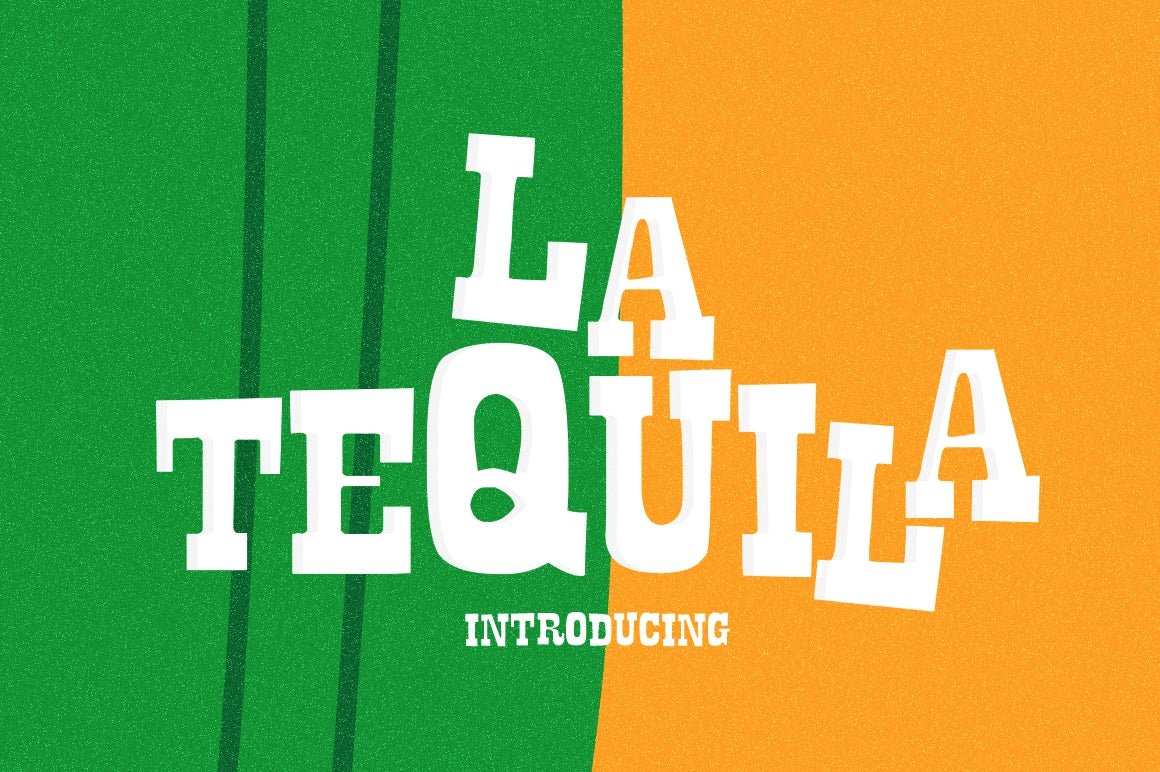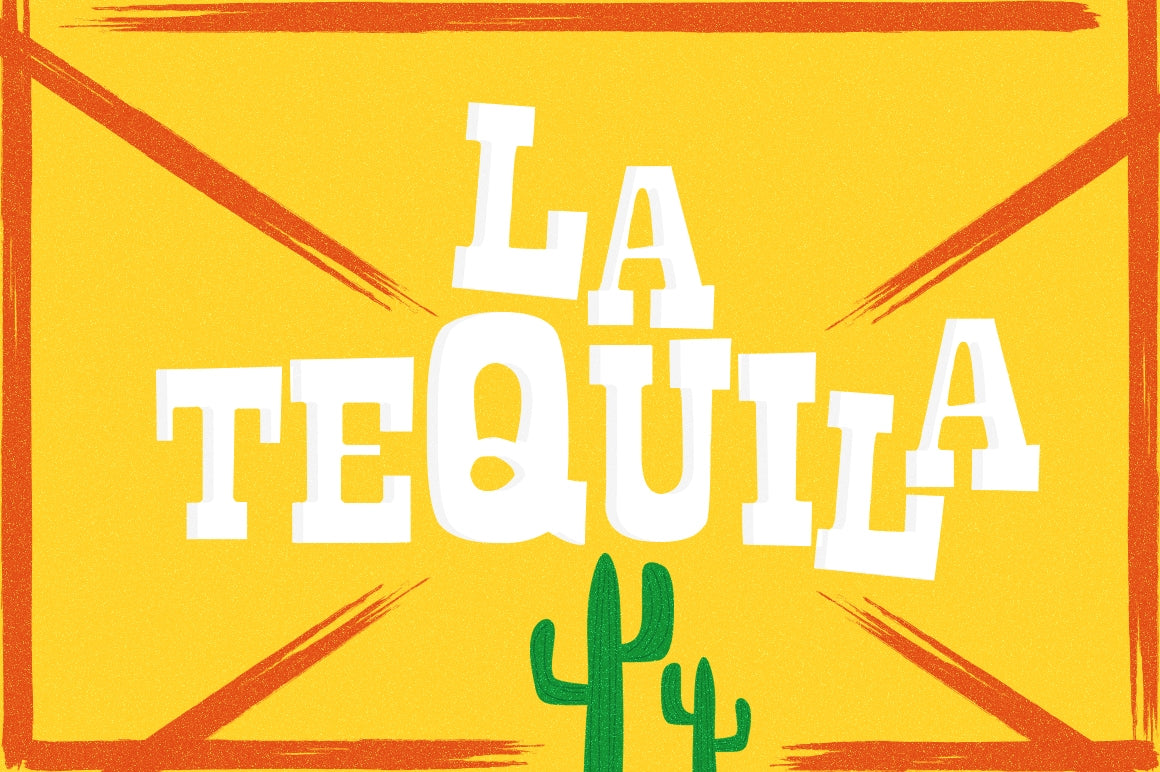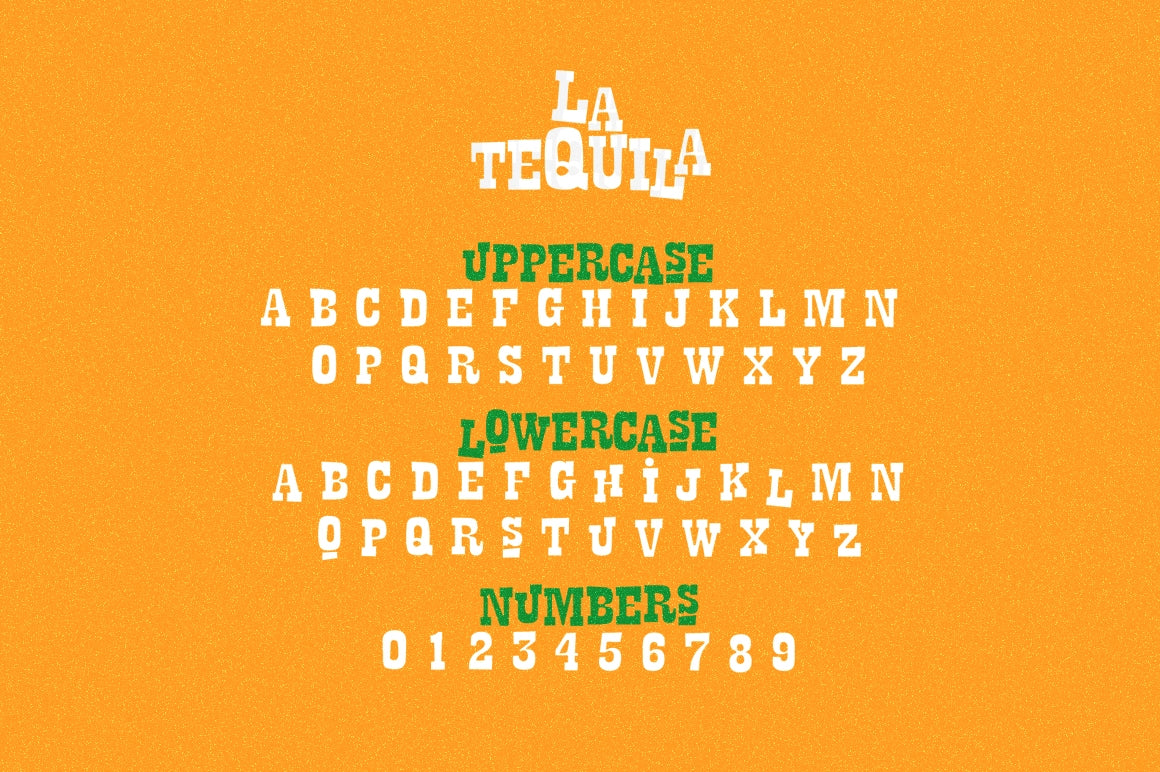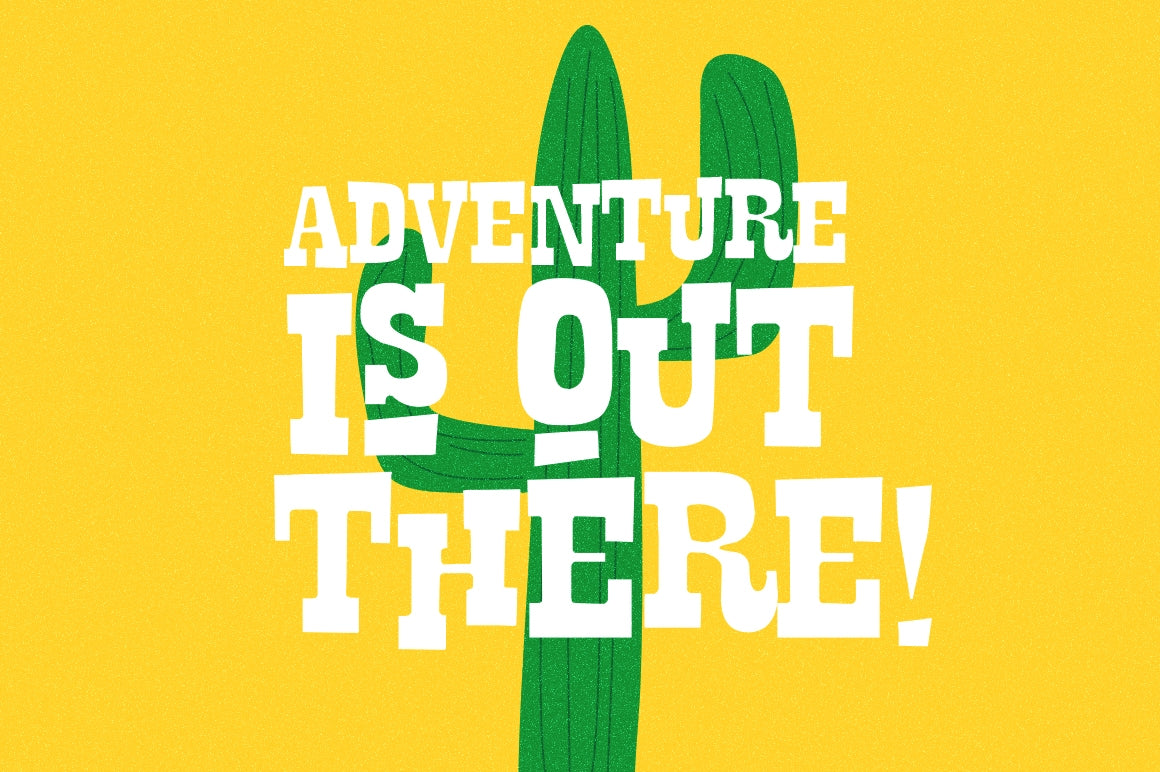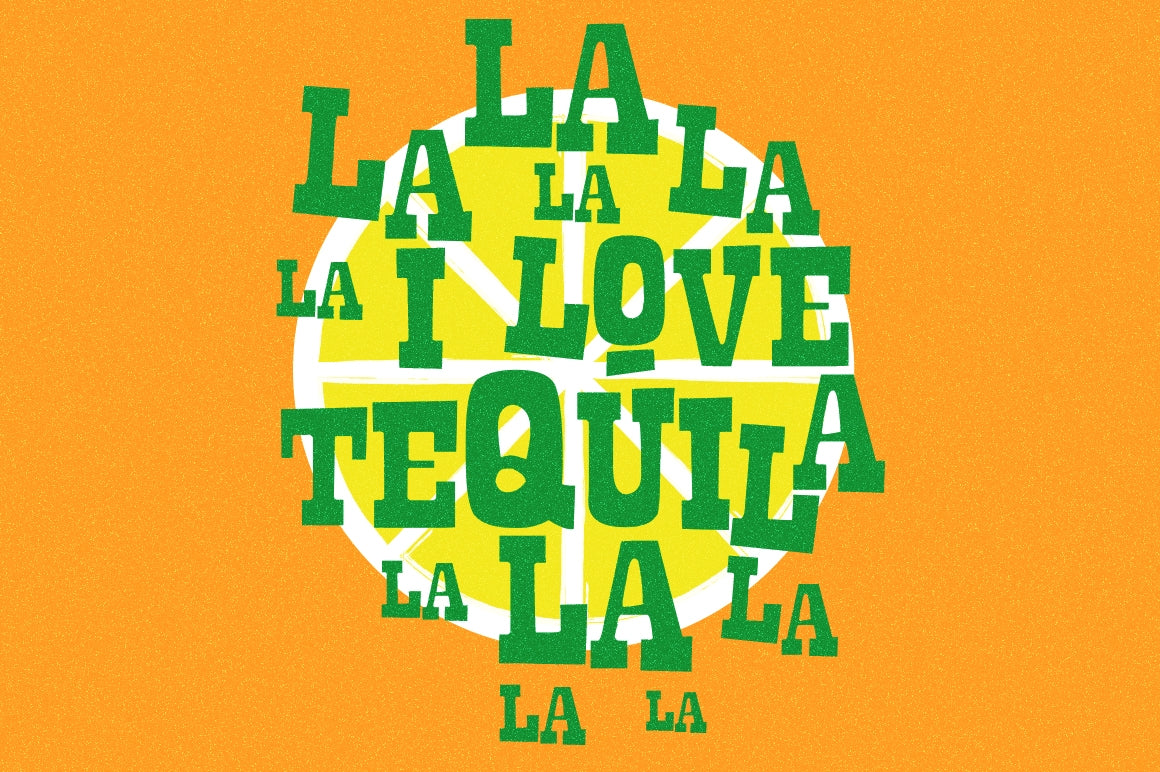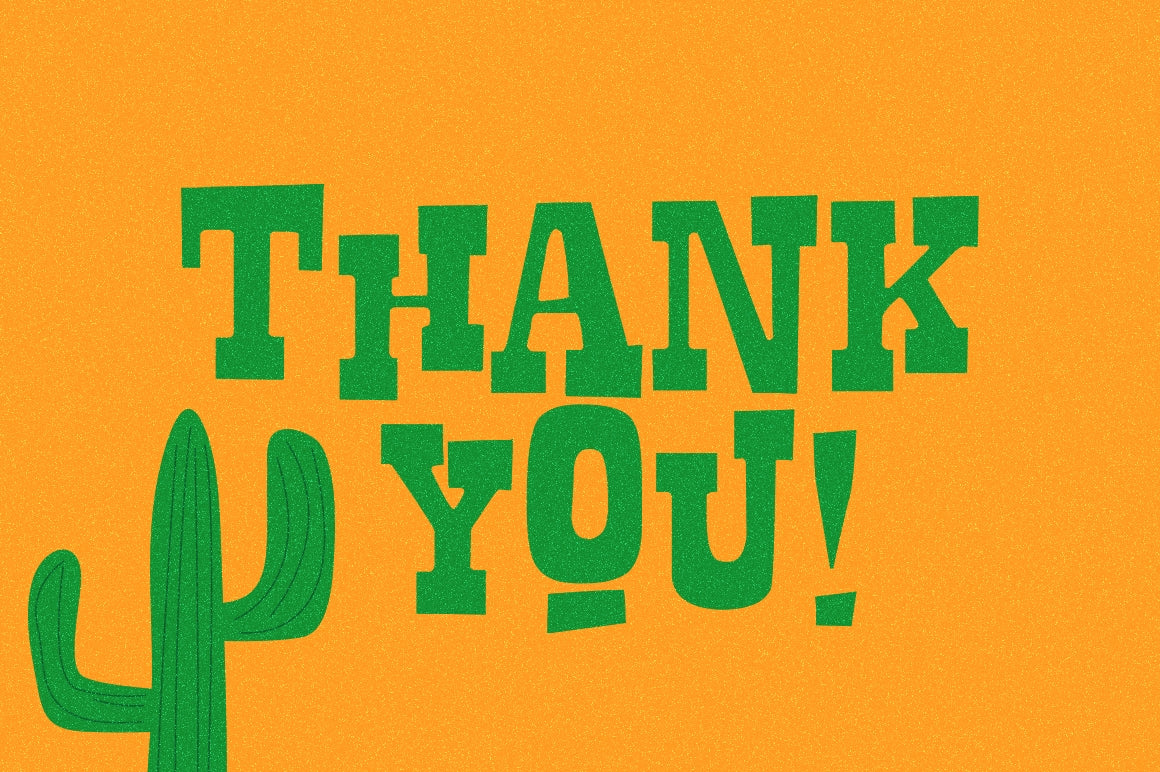
Tipografía La Tequila
La característica de estas fuentes será crear un ambiente divertido.
La fuente se puede usar para muchos propósitos, pero queda genial en carteles, camisetas o tarjetas. Además, queda perfecta en diseños con temática veraniega.